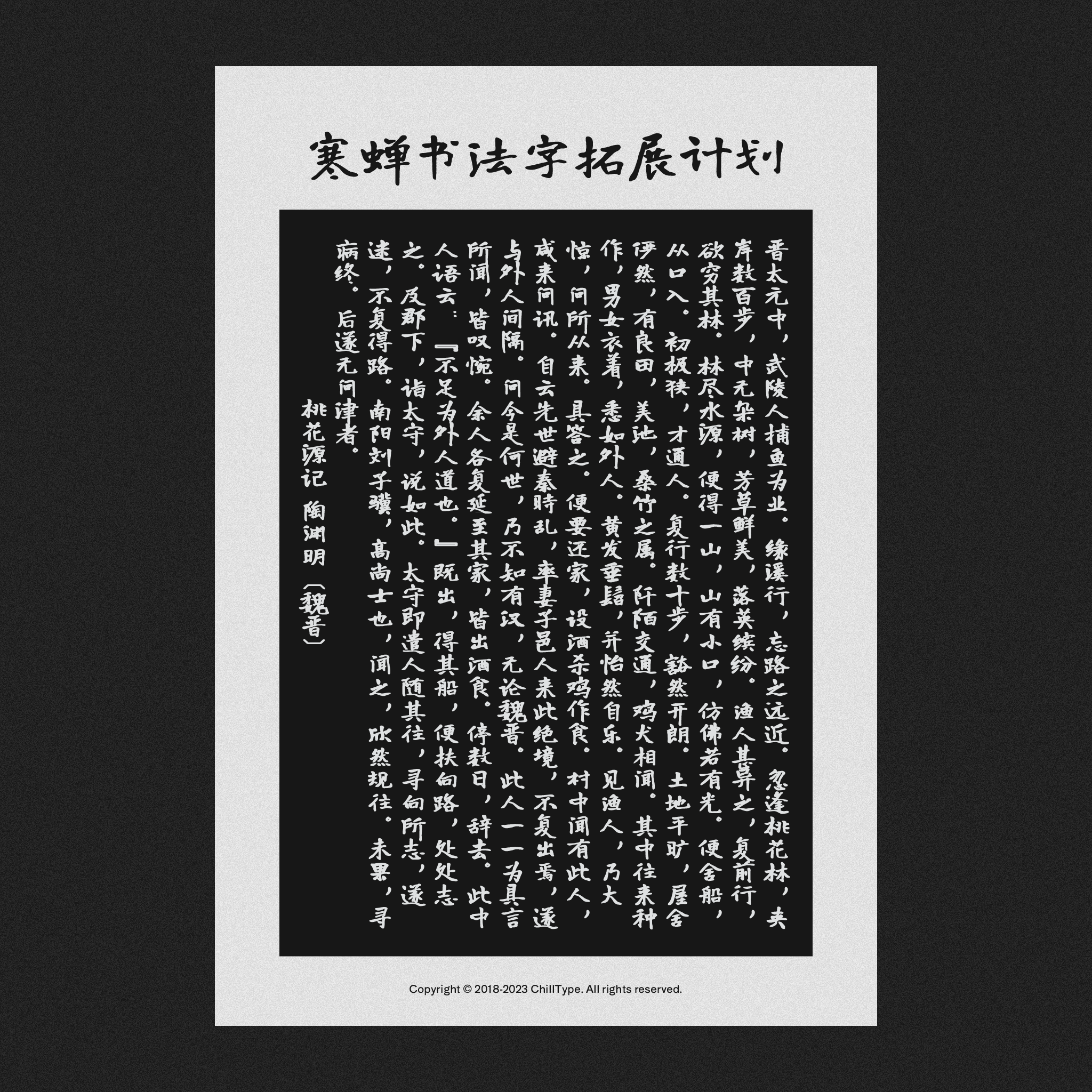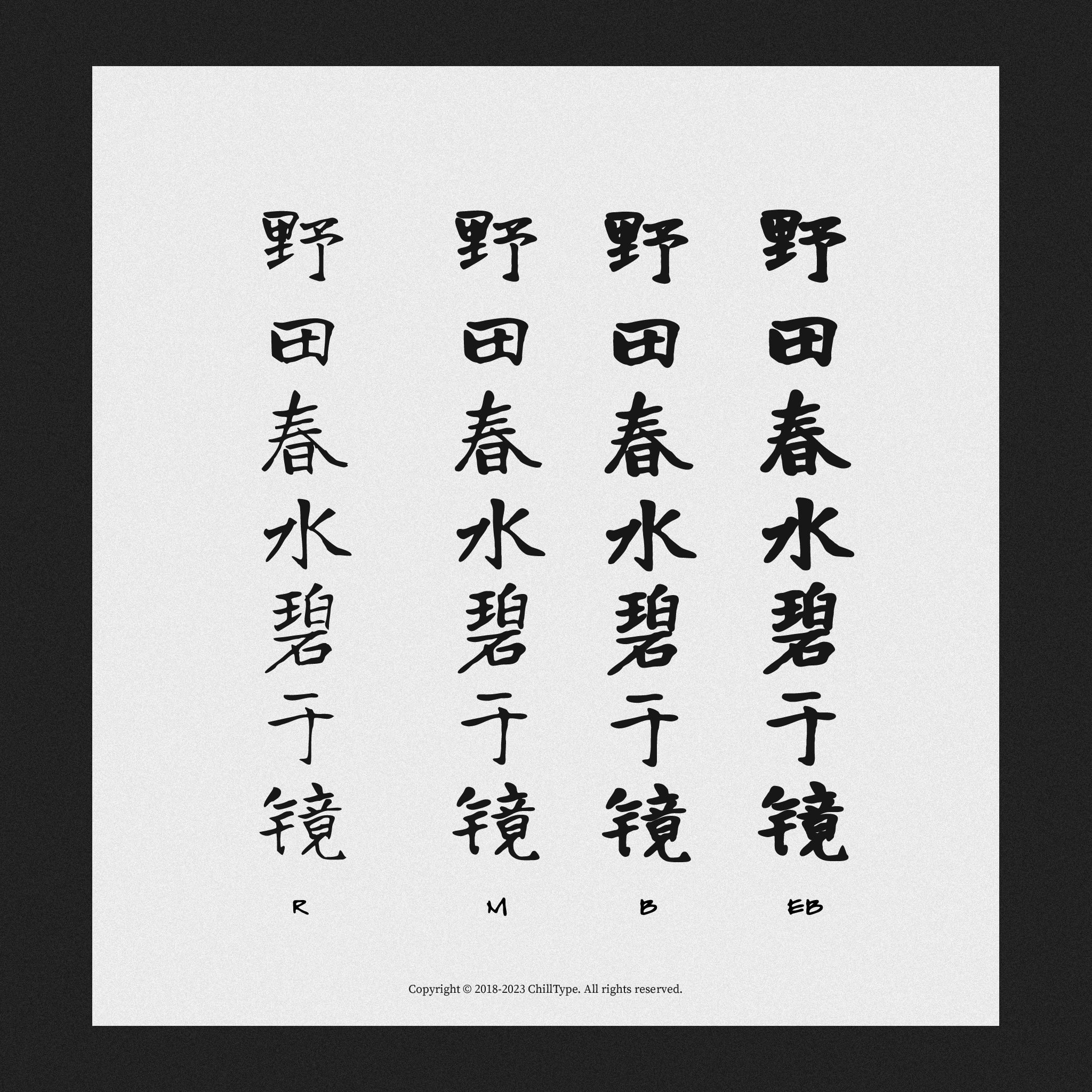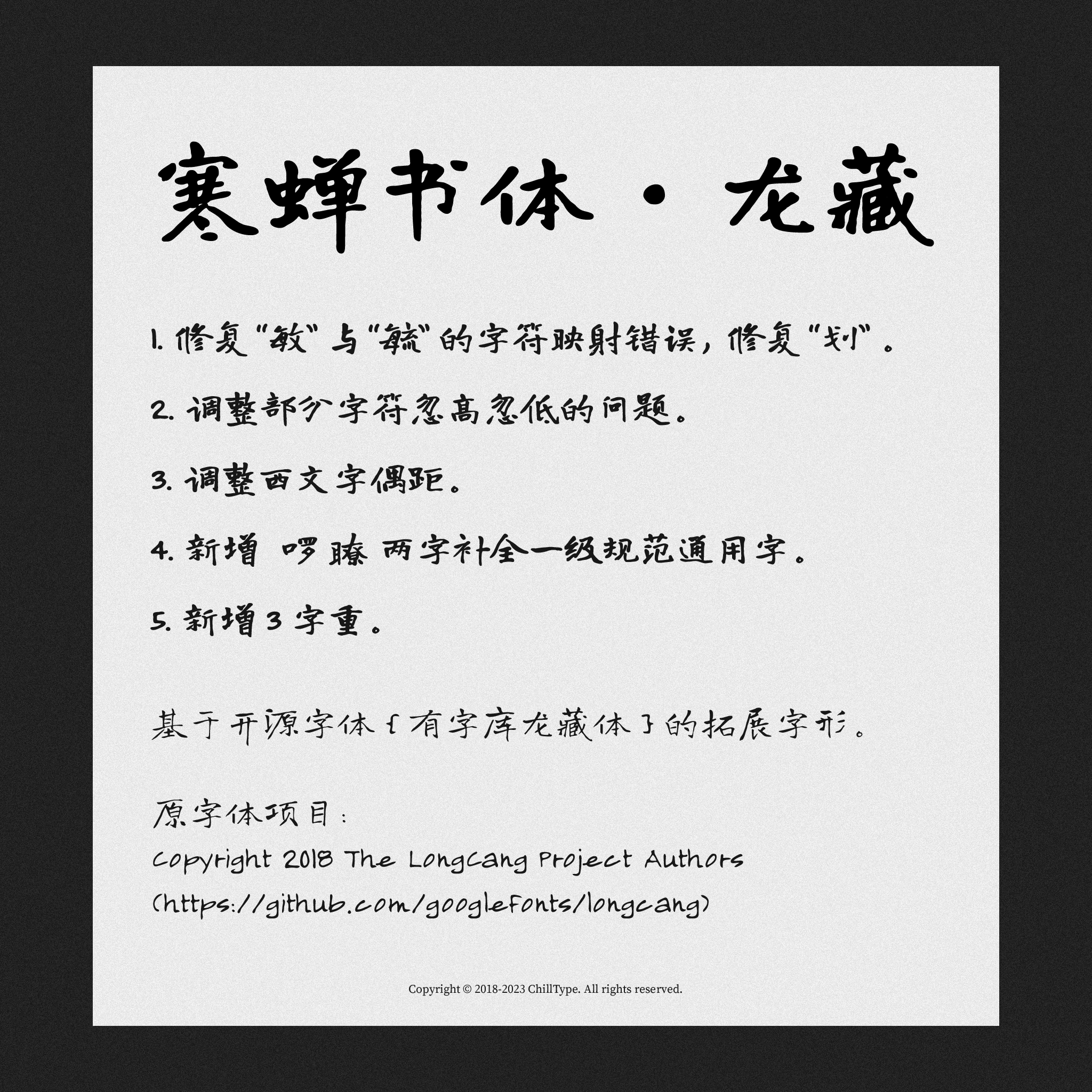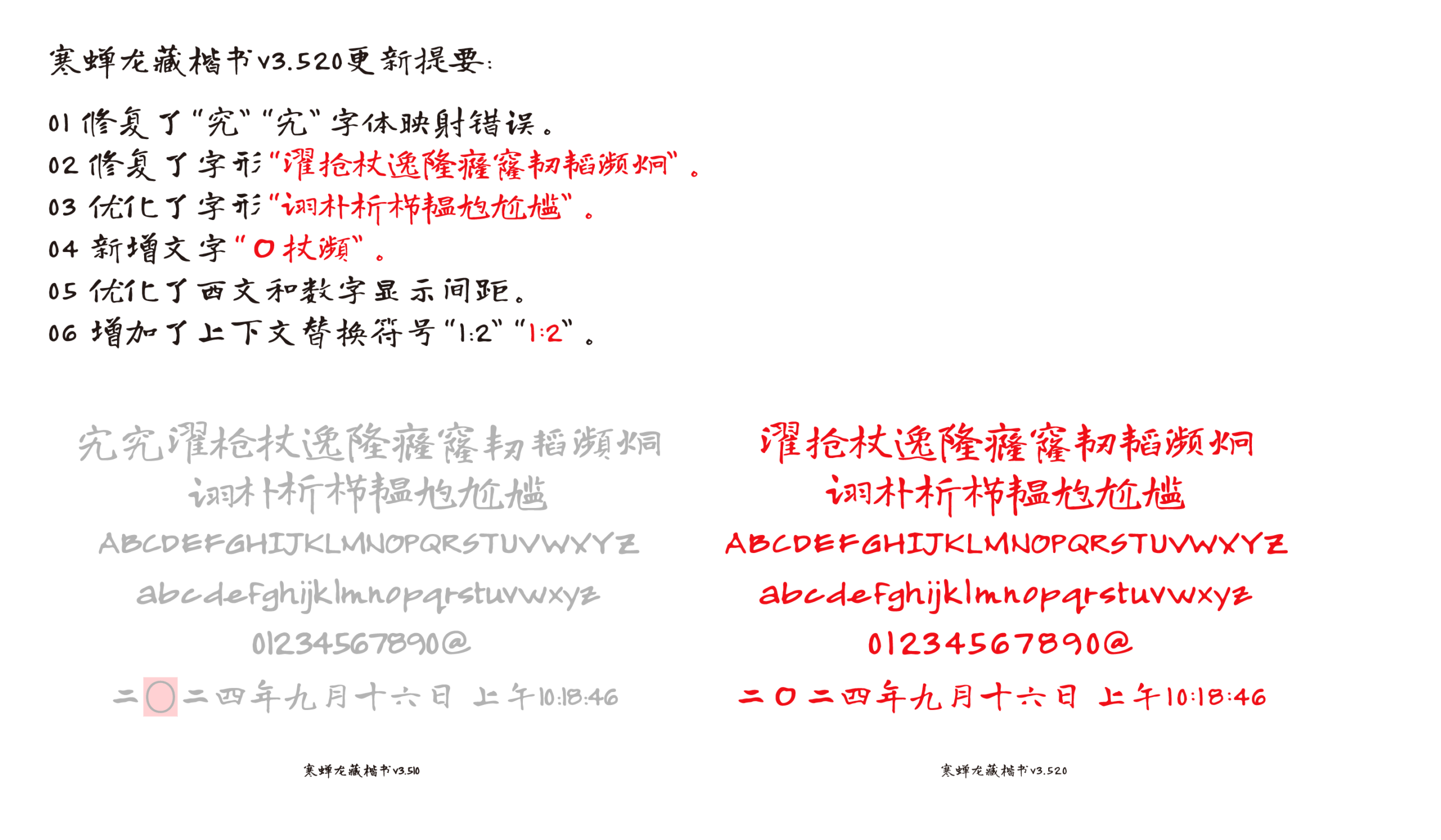
寒蝉龙藏楷书 基于开源字体{有字库龙藏体}的拓展字形。这款字体继承了原版龙藏体的优雅笔触和书法韵味,同时扩展了更多的字形和符号,以适应现代排版和数字媒体的需求。它特别适合用于传统风格的书籍、艺术作品或网页设计,为用户提供更丰富的选择。原字体项目:Copyright 2018 The LongCang Project Authors (https://github.com/googlefonts/longcang) 该开源项目由 Google Fonts 社区维护,旨在创建高质量的中文可变字体,支持多种字重和样式。项目遵循开源协议,鼓励开发者和设计师共同参与改进和扩展。
寒蝉书法字拓展计划的书法作品,呈现了陶渊明《桃花源记》的全文。
四组“野田春水碧于镜”书法字样,下方分别标注字母R、M、B、EB。
寒蝉书体·龙藏字体更新说明,含修复字符映射、调整字间距、新增字形与字重等改进,基于有字库龙藏体拓展。
v3.520 更新提要,包括修复字体映射、优化字形、新增文字、调整显示间距和增加上下文替换符号,并展示更新后的字体效果示例。